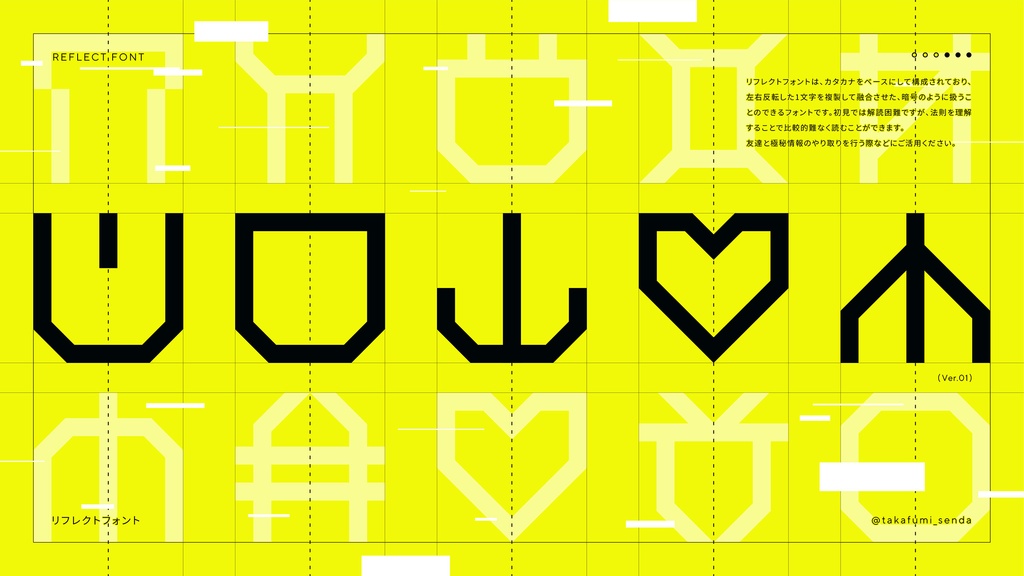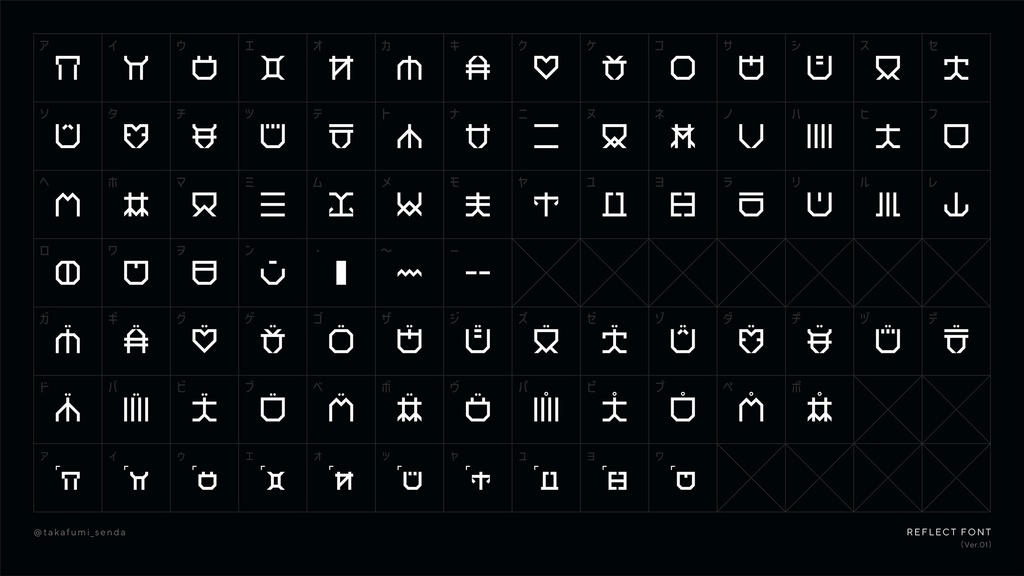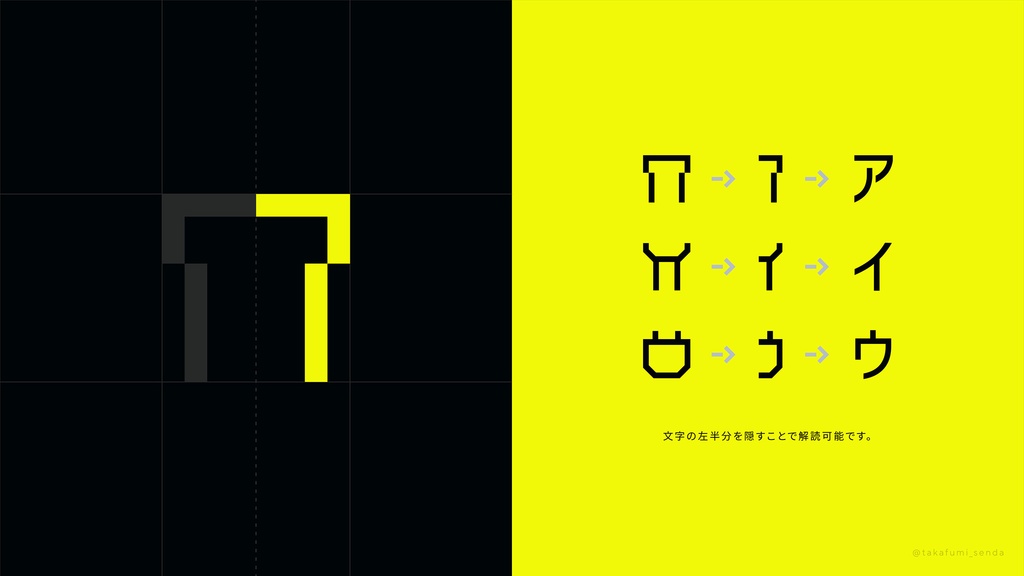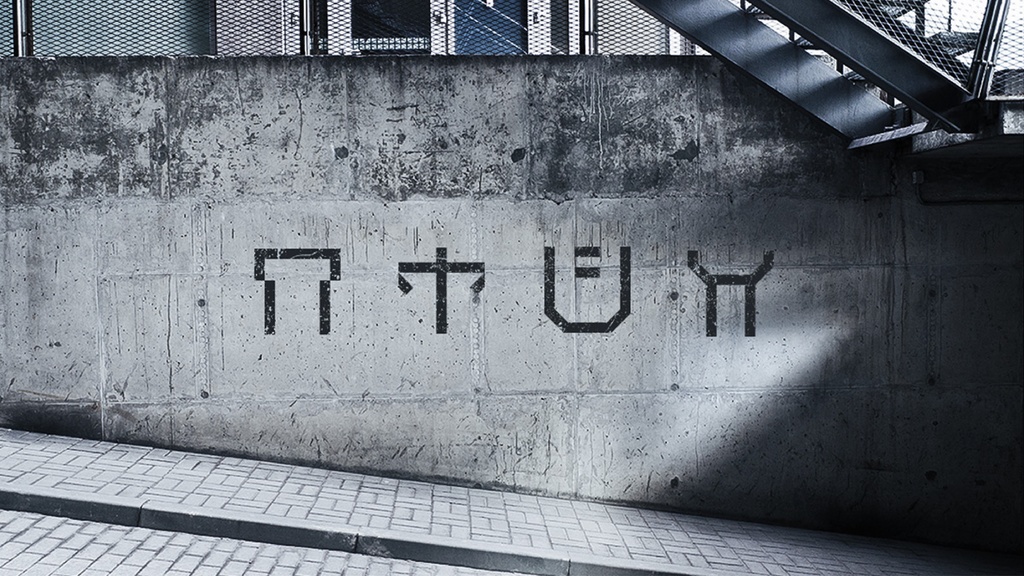
リフレクトフォント
「リフレクトフォント」は、カタカナをベースにして構成された暗号文字です。カタカナを複製して左右反転させたものを融合したような作りとなっており、初見の人からすると解読困難ですが、法則を理解した人であれば比較的難なく読むことができるというのが特徴です。 お友達と極秘情報のやり取りを行う際などにご活用ください。 ▼作者のポートフォリオサイトからもダウンロード可能です。 https://takafumisenda.com/typeface ▼Xアカウント(ポストページ) https://x.com/takafumi_senda/status/1753963415075525014?s=20 --- 必ず以下の利用規約に目を通していただいた上で、当フォントをご使用くださいますよう、よろしくお願い致します。 また、ダウンロードした時点で以下の利用規約に同意したものとみなします。 【利用規約】 ・商用、非商用問わず使用することが可能です。 ・商用利用の場合は制作者のXアカウント(https://twitter.com/takafumi_senda)のフォローが条件となります。 ・作者は著作権を放棄しておりません。自作発言はご遠慮願います。 ・当フォントを使用した際に発生したトラブルや損害についても、作者は一切の責任を負いません。 【禁止事項】 ・当書体を使用したロゴなどの商標登録、意匠登録。 ・フォントデータの改変、無断転載、再配布、販売。 ※Webフォント化やアプリへの埋め込み、書籍等への収録を希望される場合は、必ず作者までご連絡ください。 【注意事項】 ・予告なしにバージョンアップを行う場合があります。 ・一部の端末、ソフトウェアでは使用できない場合があります。